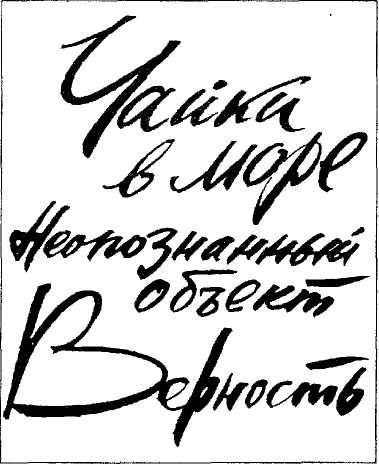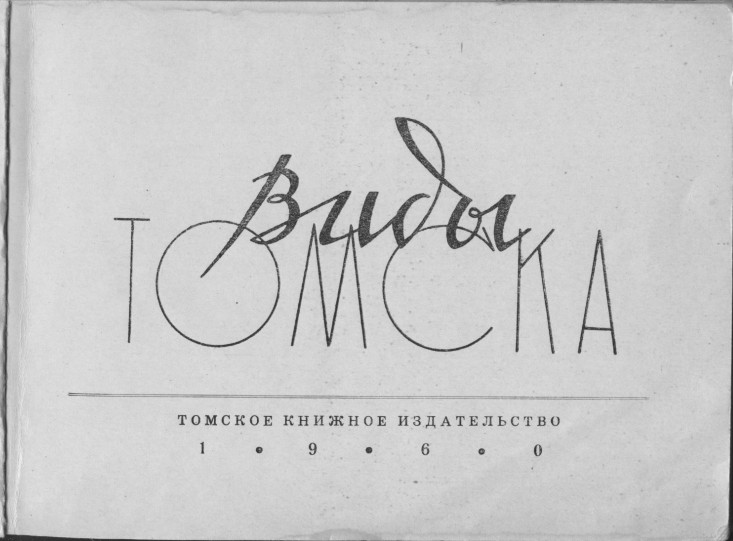
10 кириллических шрифтов, чтобы подписывать открытки и подарки
Делимся ссылками на десяток кириллических шрифтов, которые пригодятся тем, кто не любит подписывать подарки, открытки и приглашения от руки.
Не все из нас обладают идеальным почерком, да и вообще любят писать от руки. Для тех, кто хотел бы набирать открытки, приглашения и бирки для подарков на компьютере, мы выбрали десять бесплатных шрифтов с поддержкой кириллицы.
Charming
Рукописный шрифт, вдохновленный старым американским леттерингом. Подойдет для приглашений на хипстерскую вечеринку с крафтовым пивом.
Komi
Этнический шрифт. Таким хорошо подписать открытку, прилагающуюся к набору травяных чаев.
Iced tea
Оптимистичный и простой шрифт, которым можно и рукодельный подарок подписать, и мотивирующий постер набрать.
Katona
Еще один рукописный шрифт, на этот раз — тонкий и нежный, очень «открыточный».
Peteroque
Вышитые крестиком буквы для самых душевных поздравлений и приглашений.
Legend
Средневековый шрифт для тематических подарков и вечеринок. Впрочем, как и остальные, его можно использовать без особого повода, ведь нам, в отличие от серьезных дизайнеров, можно «играть со шрифтами» как угодно.
Barkentina
Элегантный шрифт для материалов в стиле ар-деко — так описывают его создатели. Понравится взрослым людям с хорошим вкусом.
Metropolis 1920
А вот это уже очевидное ар-деко: огни большого города, небоскребы, шикарная жизнь. Используйте, если собираетесь закатить вечеринку в стиле «Великого Гэтсби».
Douchepac
Экспериментальный иронический пиксельный шрифт, будто специально созданный для приглашений. Пробуйте разные цвета и сочетания обычного и жирного начертания.
Chehov
Русский шрифт, созданный специально для кириллицы. К сожалению, из знаков препинания только точка и запятая.
Chava
И еще один пиксельный шрифт, попроще, чем Douchepac.
шрифтыСоветские плакатные шрифты. Мир «ВКонтакте» Что такое советский леттеринг и как он появился
Как только я начал серьезно заниматься дизайном, сразу стал обращать больше внимания и на шрифты: от современной типографики до вязи, от экспрессивной каллиграфии до швейцарской школы. Тогда я и познакомился с советским леттерингом, и тут же захотелось создать паблик с уникальной темой и контентом. Так родился «Советский леттеринг» . Образцы советской шрифтовой школы в интернете можно было собирать только по крупицам: рыться в подборках кинотитров, просматривать старые фотографии или изучать диафильмы. А это сообщество было создано, чтобы собрать весь пласт культуры в одном месте.
Для себя я выделил 3 основных причины появления советской шрифтовой культуры.
Революция и художники-авангардисты
Дух нового времени требовал новой графики. Тени, блики, рюшечки и витиеватые шрифты были выкинуты в корзину за ненадобностью, а им на смену пришли четкие формы и минимум цветов.
Железный занавес
Советские дизайнеры имели очень ограниченный доступ к информации извне и не могли в полной мере вдохновляться работами иностранных коллег. Они варились в собственном соку. Казалось бы, создались все условия для угасания и деградации шрифтовой культуры. Но здесь нам очень повезло с художниками-оформителями, которые при таком положении вещей не стояли на месте, а, наоборот, темпами советской промышленности развивали новую шрифтовую культуру.
Стандарт 1337 «Шрифты гартовые»
В 1930 году в СССР произошло важное для всей полиграфической промышленности событие. В феврале Всесоюзным комитетом по стандартизации был принят обязательный Общесоюзный стандарт 1337 «Шрифты гартовые».
Этот небольшой двухстраничный документ ограничил советских дизайнеров определенным набором шрифтов (всего 20 гарнитур и 31 начертание). Сюда вошли гарнитуры «Обыкновенная», «Учебная», «Латинская» и т.д. Все шрифты, не вошедшие в список, должны были быть отправлены на переплавку. Советским художникам-оформителям не хотелось ограничивать себя в выразительных средствах и верстать все книги по одному стандарту. Поэтому многие взяли в руки карандаши, кисти, перья и начали восполнять недостаток шрифтов, создавая свои уникальные авторские композиции. Каждый тот эксперимент с каллиграфией, по сути, уникален, но фиксировать и систематизировать их стали только к 1960-м, когда начали появляться первые каталоги шрифтов.
Шрифт как неотъемлемая часть культуры
Невозможно себе представить советскую улицу без неоновой вывески «Универмаг», советское кино без динамичных, размашистых титров, советскую книгу без красивой минималистичной обложки или советский плакат без фирменной узнаваемой графики.
Шрифт был неразрывно связан с культурой и историей.
В паблике уже несколько тысяч человек, и многие из них предлагают в новости свои фотографии. Кому-то понравилась старая вывеска в деревне у бабушки, кто-то взял в библиотеке старую книгу и восхитился обложкой, а кто-то фотографирует старый холодильник дома у родителей. Все это превращает страницу в библиотеку уникального контента. Очень отрадно, что люди неравнодушны к этой исчезающей культуре.